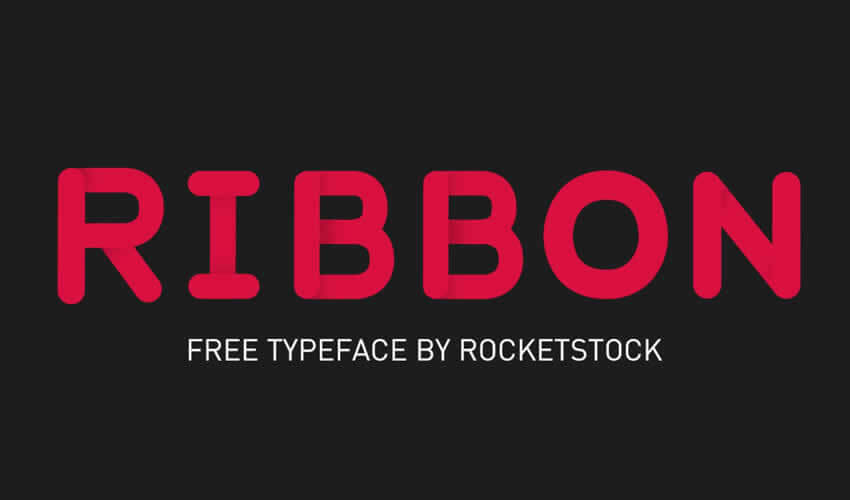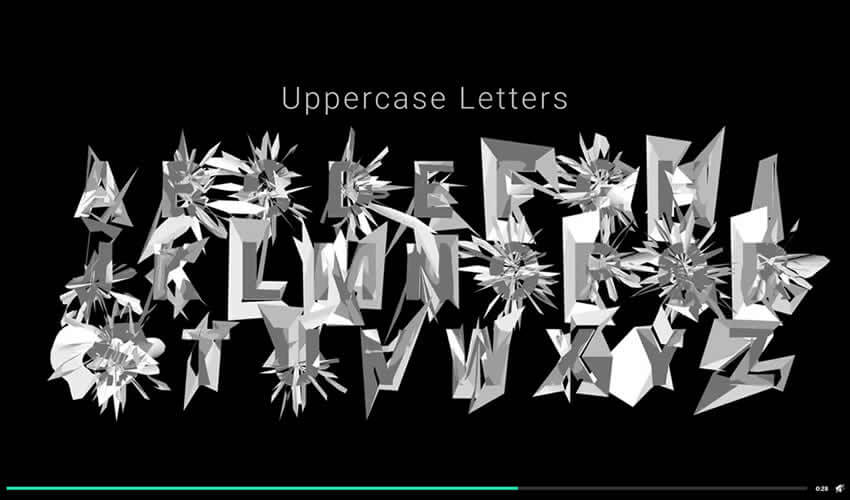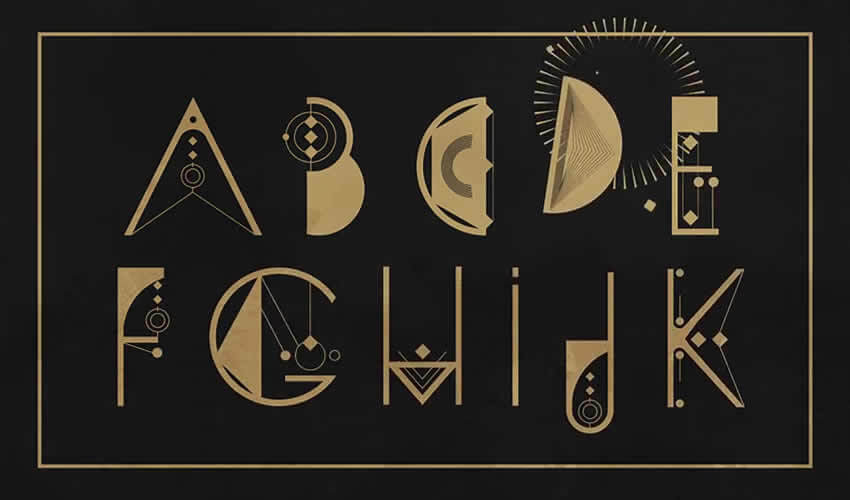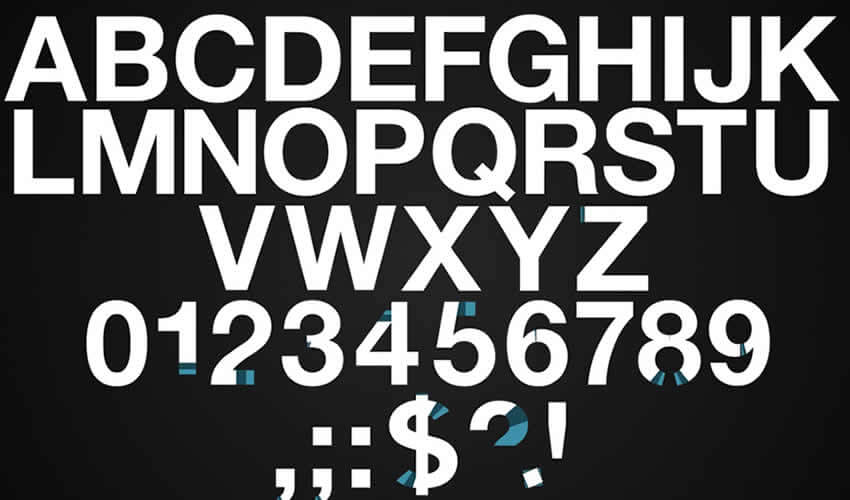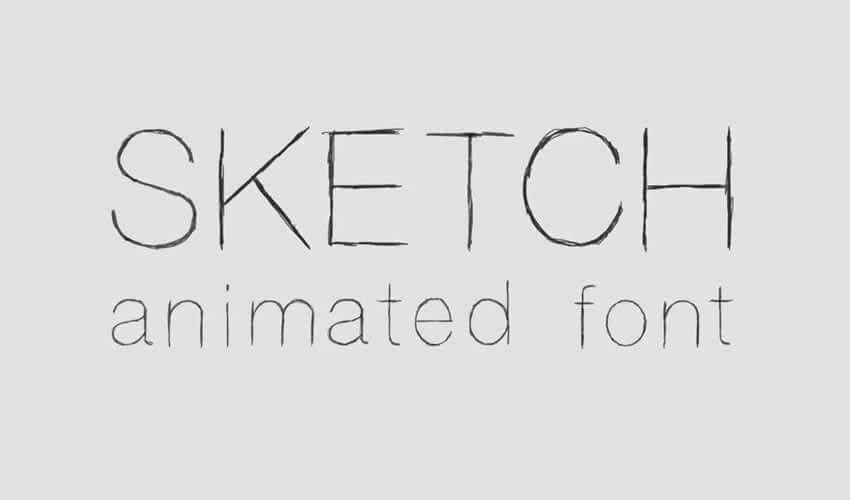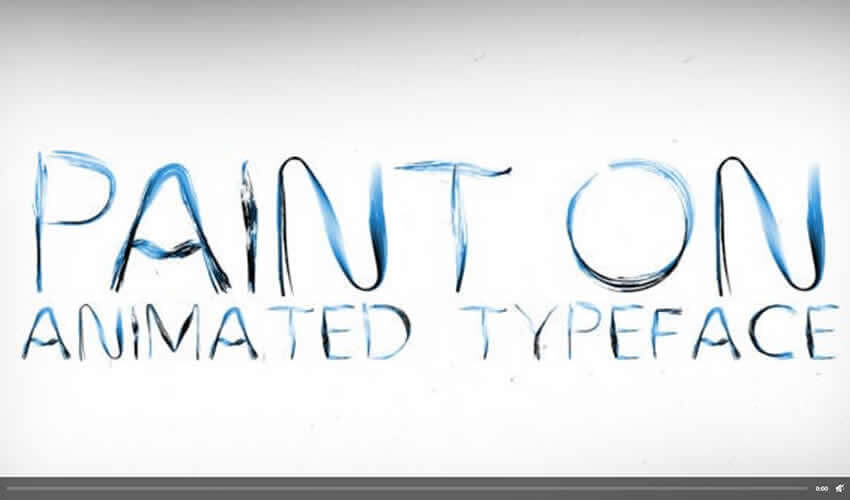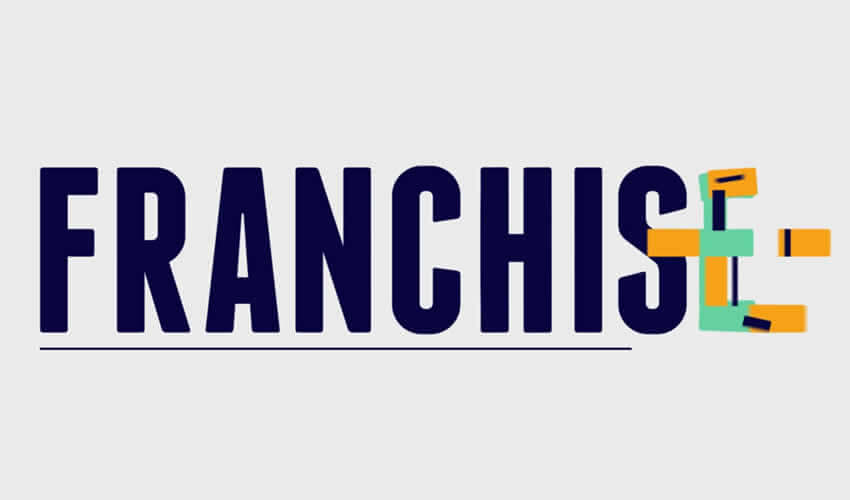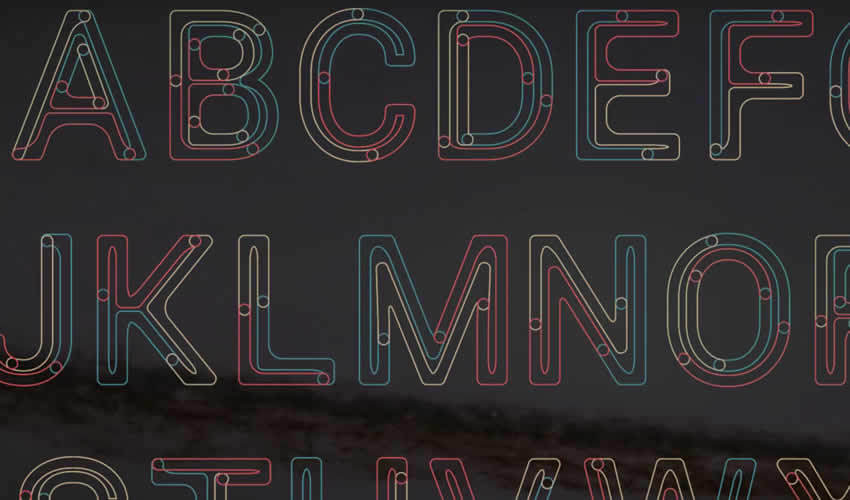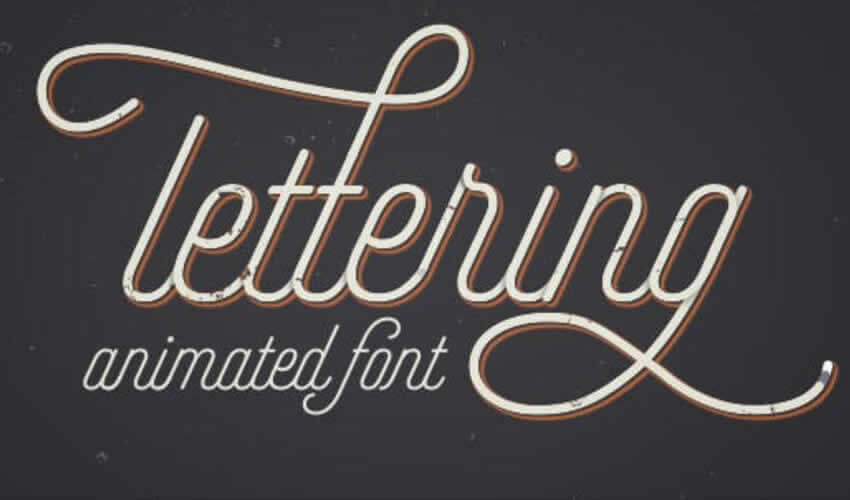
アニメーションの書体は、タイトルアニメーションを最初から作成する手間をかけずに、ビデオタイトルを盛り上げるのに最適な方法です。
幸いなことに、ビデオプロジェクトで使用できる、アニメーション化された書体がオンラインで利用可能です。 ハイテクアニメーションの書体から、遊び心のあるレトロなスタイルの書体まで、あらゆるタイプのビデオにアニメーションの書体があります。
この投稿では、ダウンロードしてプロジェクトで使い始めることができる、Web全体から最高のアニメーションの書体を集めました。
Ribbon Free Animated Typeface for Editors (無料)
リボンの書体は、風変わりで楽しいデザインで、若い聴衆を対象とするブランドやビジネスに適しています。 78のキャラクターと事前にレンダリングされたクリップを取得します。
PolyNoise Alphabet Animated Typeface (Envato Elementsを使用)
リストの最初のアニメーション化された書体はグリッチのある外観を備えているため、グリッチのあるアニメーションを使用するビデオに最適です。 色は簡単にカスタマイズでき、この書体を使用すると、各文字を別々のタイムラインにドロップする心配がありません。
Alquimia Animated Font on Behance (無料)
Alquimiaアニメーションフォントは、本当にユニークな外観です。 フォントは個人プロジェクトと商業プロジェクトの両方で自由に使用でき、色を簡単に変更できます。
Paper – Grotesque Shady Animated Typeface (Envato Elementsを使用)
ペーパーは、クリエイティブなタッチが必要なビデオに取り組んでいる場合に最適です。 フォントには、完全なアルファベットのほか、数字、基本的な通貨記号、基本的な数学記号が含まれています。
Helvetica Neue Free After Effects Template (無料)
クラシックなタッチが必要な次のプロジェクトで、Helvetica Neueアニメーションフォントを検討してください。 このフォントテンプレートは、43の一意の文字、数字、および句読点の構成を備えたAfter Effectsテンプレートです。
Sketch Animated Font After Effects Template (無料)
手書きのルックアンドフィールが必要な場合は、スケッチアニメーションフォントが最適です。 フォントには、大文字、小文字、数字、句読点が含まれます。
Paint on Animated Typeface (Envato Elementsを使用)
動画にユニークな外観を追加したい場合、Pain Onアニメーションタイプフェイスは必須です。 各キャラクターは白、黒、青の色でペイントされ、簡単にブランドカラーにカスタマイズできます。
Animography Animated Font for AE (無料)
Animographyアニメーションフォントは、110人のアニメーターと1人のデザイナーの共同プロジェクトとして生まれたフル機能のアニメーションフォントです。 フォントははっきりとした大胆な外観で、企業のビデオに使用できます。
Alphabet Free Animated Font and AE Project (無料)
このカラフルで注目を集めるアニメーションフォントは、Robotoと呼ばれるオープンソースのGoogleフォントに基づいています。 各文字は個別のファイルであり、各文字を自分のプロジェクトに簡単にドラッグアンドドロップできます。
Animated Lettering Font (Envato Elementsを使用)
アニメーションのレタリングフォントは、結婚式のビデオや、ハイエンドのファッションやジュエリー会社を宣伝するビデオに最適です。 フォントには、完全なアルファベットと数字、およびさまざまな異なるスタイルが含まれています。
キネティックタイポグラフィは、最初からアニメーションタイトルを作成する必要なく、視覚的な魅力を追加できるため、どのビデオプロジェクトにも最適です。 このリストを使用して、次のビデオプロジェクトに最適なアニメーションの書体を見つけてみてくださいね。